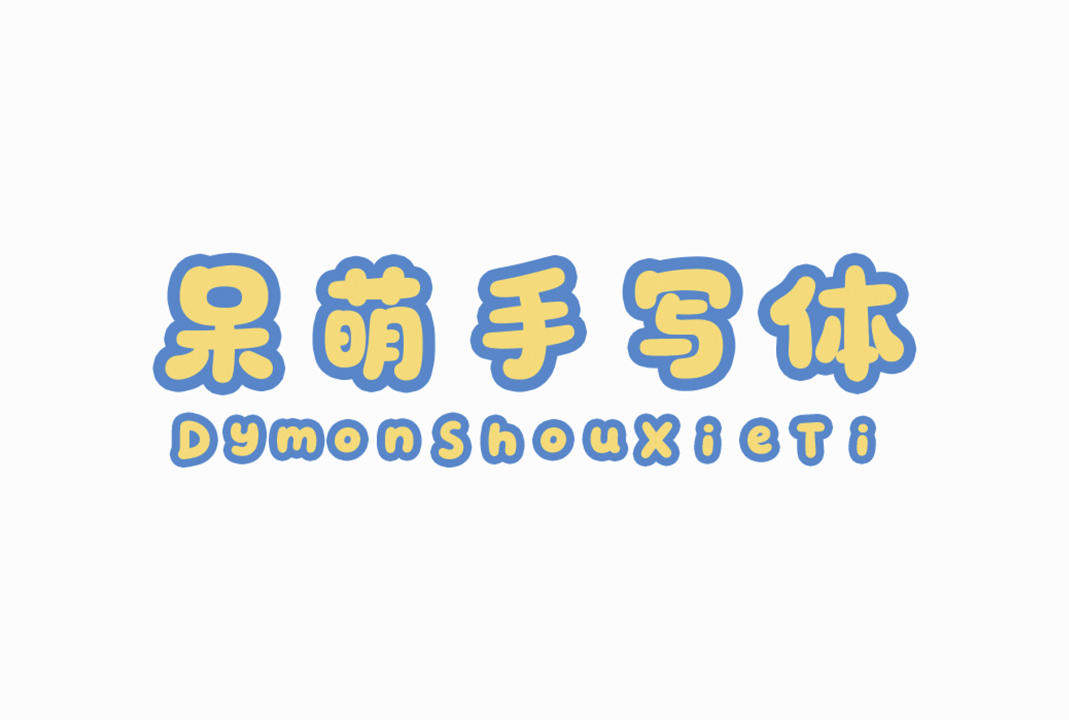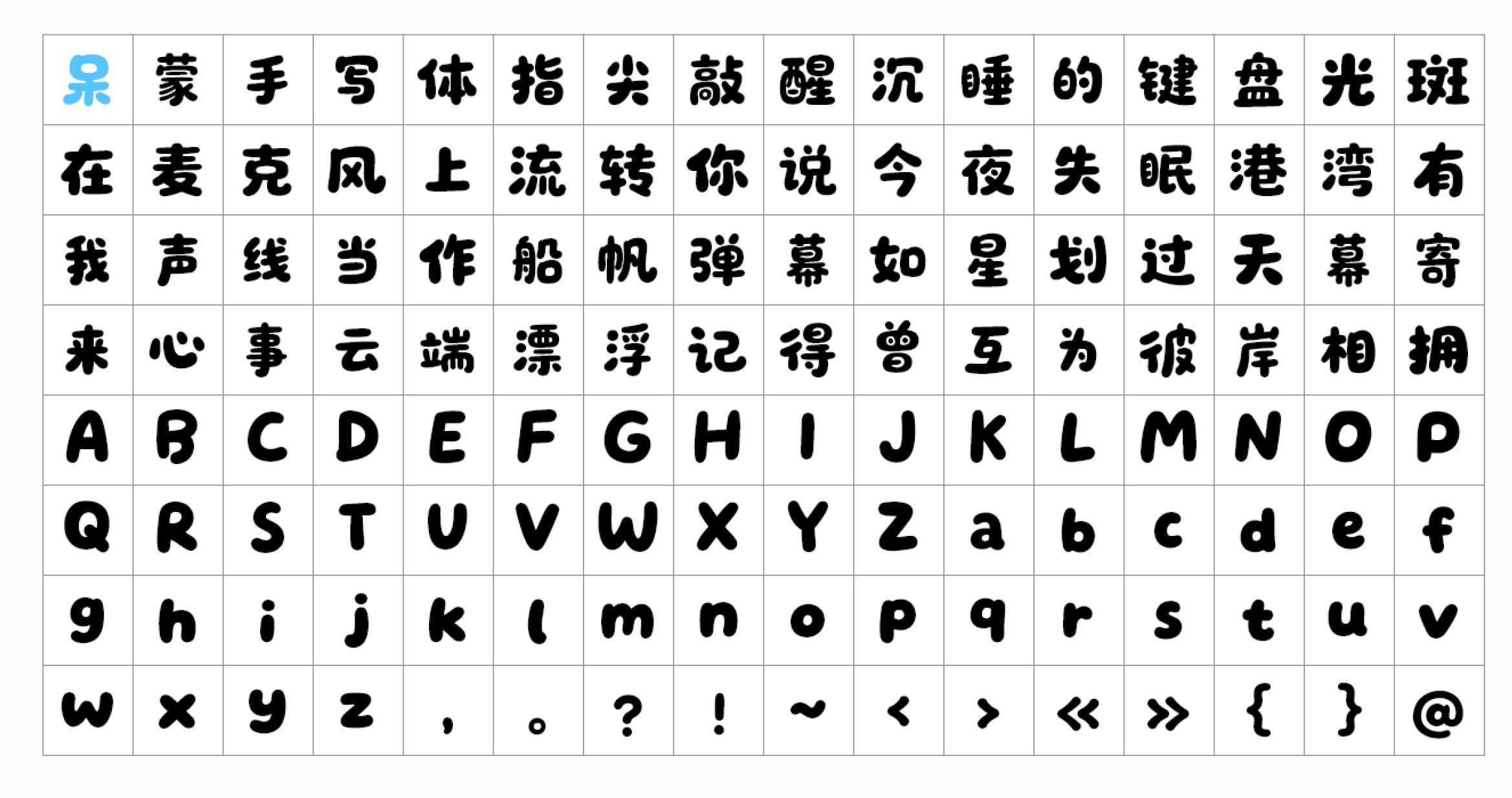
呆萌手写体 (Dymon-ShouXieTi) 中文免费卡通风格字体下载
呆萌手写体 (Dymon-ShouXieTi) 曲线Q弹、造型圆润与稚拙的笔划结构相映成趣,通过灵动的连笔转折与适度的墨迹留痕,营造出充满童真的视觉韵律。
呆萌手写体 (Dymon-ShouXieTi) 收录常用中文汉字及基础符号,可满足日常商业设计、文创产品、网络传播等多场景应用需求。